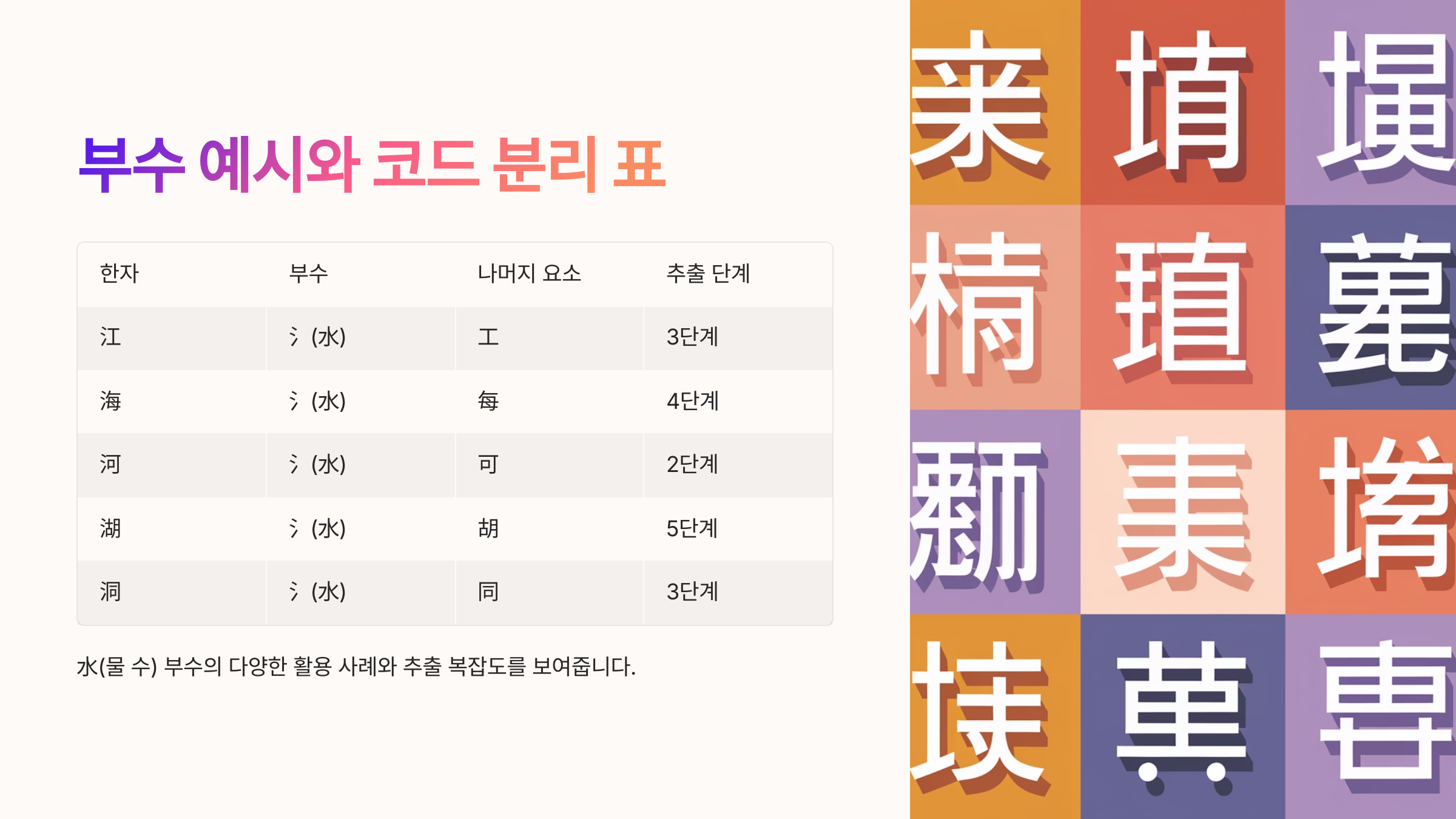
한자는 복잡한 구성과 수천 년의 역사를 가진 문자예요. 그 구조의 핵심 중 하나가 바로 '부수(部首)'인데요, 부수는 사전에서 한자를 찾을 때 가장 많이 쓰이는 기준이에요. 이 부수를 자동으로 추출해내는 스크립트를 만들면, 데이터 처리나 학습 도구를 만드는 데 큰 도움이 되죠.
내가 생각했을 때, 이건 자연어처리와 전통 언어학이 만나는 흥미로운 분야라고 느껴져요. 부수는 단어의 의미를 짐작하게 해줄 뿐만 아니라 컴퓨터가 한자를 분류하거나 검색하는 데도 아주 중요한 역할을 해요.
자, 그럼 본격적으로 부수를 자동으로 분리하는 스크립트를 어떻게 만드는지 하나씩 알아볼게요. 초보자도 따라할 수 있도록 설명해 볼게요 😊
🧩 부수의 개념과 중요성
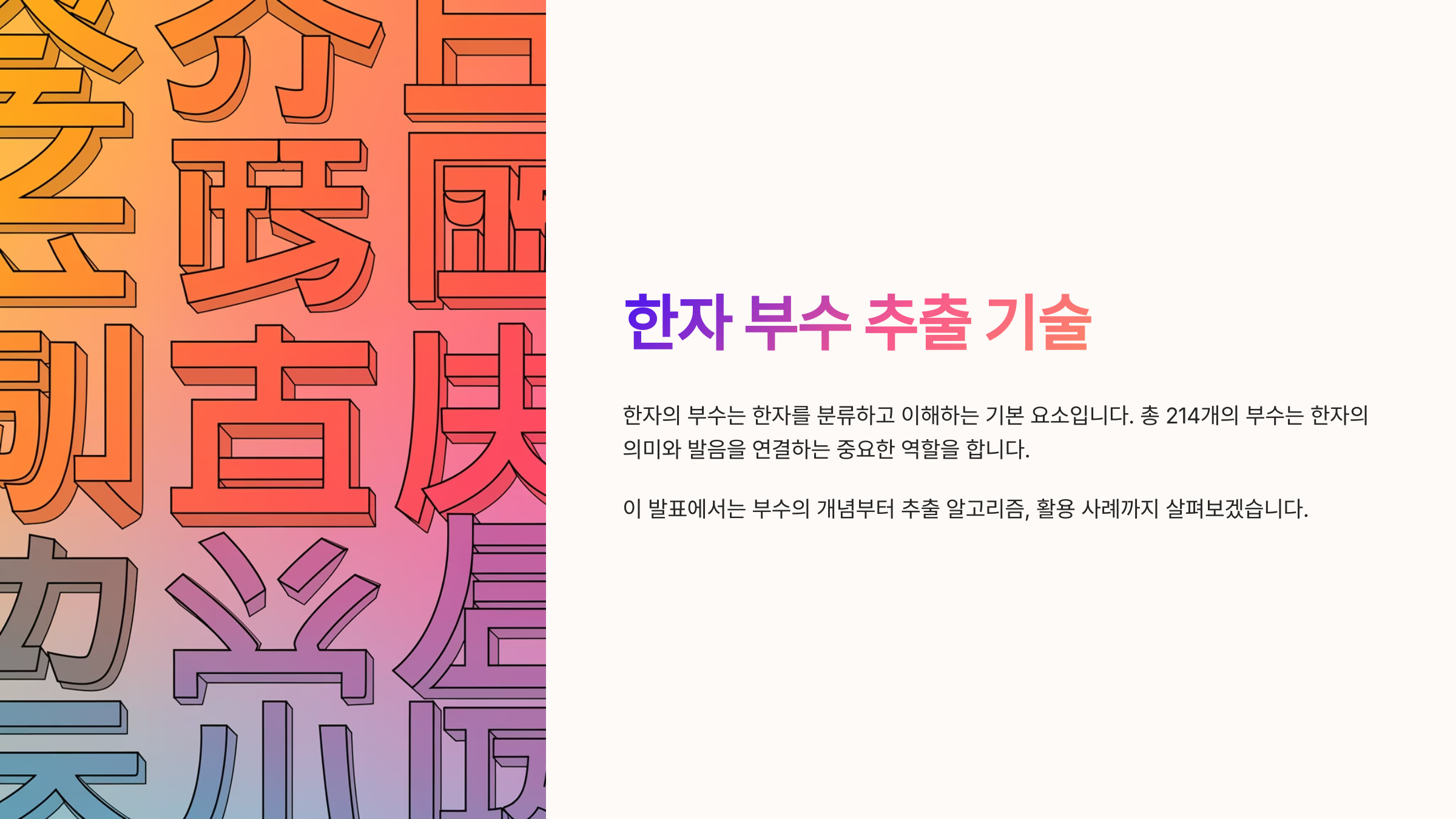
한자의 '부수(部首)'는 기본 구성 요소로, 전체 한자를 분류하고 정리하는 기준이 되는 부분이에요. 예를 들어 '河(물 하)'라는 글자는 '氵(삼수변)'이 부수로, 물과 관련된 의미를 암시하죠. 이런 식으로 한자의 의미나 유래를 이해하는 데 아주 유용한 단서가 되는 것이 바로 부수랍니다.
중국어나 일본어, 한국어에서도 한자를 분류할 때 사전마다 부수 체계가 쓰여요. 따라서 부수를 정확하게 파악하고 자동화하는 건 교육용 시스템이나 전자사전, OCR 인식 시스템 등 다양한 분야에서 꼭 필요해요.
현재 대부분의 부수 분리는 수동으로 이뤄지거나, 데이터베이스에 의존해요. 하지만 대량의 한자를 자동 분석해야 할 때는 프로그래밍 기반 접근 방식이 훨씬 효율적이랍니다.
부수는 보통 214개로 분류되며, 각 부수는 그 안에 수천 개의 파생 한자를 포함해요. 따라서 정확한 분리 규칙을 세우는 것이 스크립트 설계의 핵심이에요.
이러한 규칙을 이해하고 코드화하면, 간단한 입력만으로도 부수와 나머지 성분을 분리하는 프로그램을 만들 수 있어요. 그리고 이건 AI 한자 학습 시스템에도 응용될 수 있어요!
다양한 한자 앱이나 필기 인식 시스템에서도 부수를 기준으로 검색 기능을 제공하고 있죠. 사용자의 편의성을 높이기 위해서라도 자동화는 필수라고 할 수 있어요.
한자의 형태학적인 구조는 시각적으로도 뚜렷하기 때문에, 이미지 인식과 결합한 부수 분석도 충분히 가능해요. 이런 융합 기술은 교육 및 번역 분야에서 강력한 도구가 될 수 있어요.
예를 들어 '木(나무 목)'이 부수인 한자들은 대체로 자연, 식물, 생태와 관련된 의미를 가지고 있어요. 이런 연관성은 AI가 단어 의미를 유추할 때도 유용하답니다 🌳
한자를 부수 중심으로 분리해두면, 검색, 정렬, 통계, 의미 분석, 데이터 시각화 등 다양한 프로젝트에 폭넓게 활용할 수 있어요.
📘 자주 쓰이는 부수 TOP 10
순위 부수 의미 대표 한자 1 氵 물 河, 海, 活 2 亻 사람 他, 使, 住 3 木 나무 林, 村, 案 4 扌 손 打, 拍, 握 5 女 여자 好, 妹, 婚 이 표처럼, 한자에서 자주 나타나는 부수를 알면 어떤 글자가 어떤 계열에 속하는지도 쉽게 파악할 수 있어요. 다음 섹션에서는 한자가 어떻게 구조화되어 있는지를 더 깊이 살펴볼게요 ✨
🔤 한자의 구성 방식 이해하기
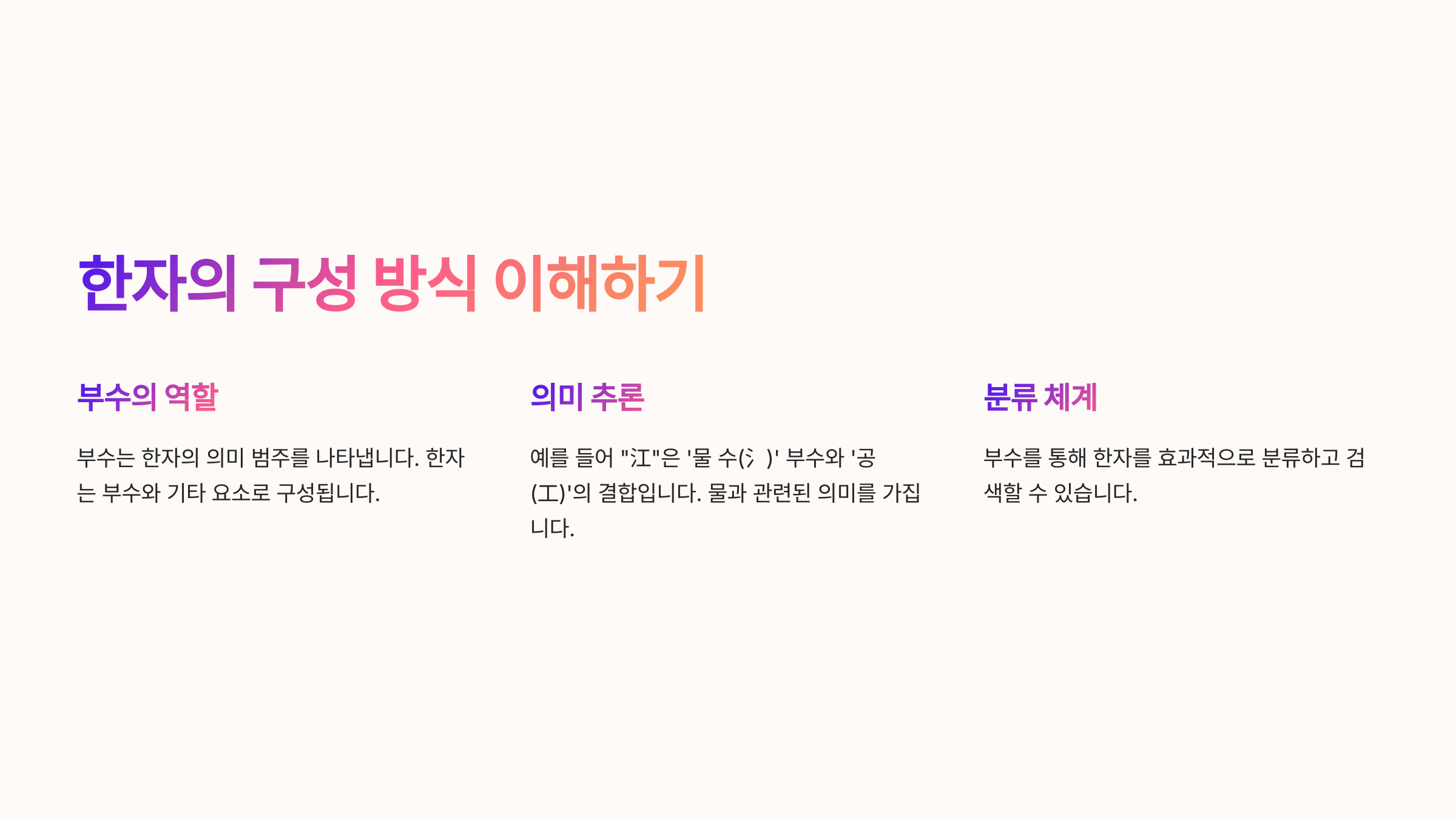
한자는 기본적으로 ‘형성 문자’와 ‘회의 문자’로 크게 나뉘어요. 형성 문자는 부수(의미를 가진 부분) + 음부(발음을 나타내는 부분)로 구성돼 있고, 전체 한자의 약 80%가 이 방식이에요. 예를 들어 ‘江(강)’은 ‘氵’는 물을 의미하고 ‘工’은 발음을 나타내죠.
이 구조를 이해하면 어떤 한자를 보더라도 "아, 이건 물과 관련 있구나" 하는 식의 해석이 가능해요. 그래서 부수는 단순한 모양이 아니라 의미의 근간이에요. 마치 단어의 뿌리와 같다고 볼 수 있죠.
또한 한자의 배치 방식도 다양한데요. 왼쪽-오른쪽 구조(좌우형), 위-아래 구조(상하형), 바깥-안 구조(외부 구조)로 나뉘어요. 이런 정보는 스크립트에서 부수를 추출할 때 위치 기반 판단을 도와줘요.
예를 들어, '休'는 왼쪽의 '亻'이 부수이고, 오른쪽의 '木'이 음부예요. 반면, '問'은 바깥쪽 ‘門’이 부수이고 안쪽의 ‘口’가 성분이에요. 이처럼 다양한 패턴을 파악하는 것이 핵심이에요.
스크립트를 만들기 위해서는 이 구성을 먼저 코드에 반영해야 해요. 한자의 유니코드 표준과 위치 정보를 결합하면 어느 정도 자동화가 가능해진답니다.
한자의 조합 방식은 규칙성이 있지만 예외도 많아요. 따라서 머신러닝보다는 사전에 정의된 규칙 테이블과 위치 기준 분석을 혼합하는 접근이 더 효율적이에요.
또한 글자의 복잡도(획수)를 기준으로 어느 성분이 부수인지 판단하는 것도 좋은 방법이에요. 예를 들어 부수는 대체로 간단한 모양이 많고, 자주 등장하는 위치에 나타나요.
여기서 중요한 건, 한자의 비율과 구조를 파악하고 이를 기준으로 필터링 로직을 설정하는 거예요. 위치, 의미, 획수, 출현 빈도를 종합적으로 고려하면 정확도가 높아져요.
특히 AI OCR 시스템을 쓸 때는 글자의 외곽 구조를 보고 부수를 인식하는 기능도 함께 적용할 수 있어요. 교육용 앱에서는 애니메이션으로 글자 구조를 설명하는 기능도 있죠 🖋
이제 이런 개념을 바탕으로, 부수를 자동으로 추출하는 알고리즘 로직을 설명해볼게요. 코딩 쪽으로 가봅시다! 🧑💻
🧠 한자 구조 유형 분류표
유형 예시 설명 좌우형 休, 明, 林 왼쪽이 부수, 오른쪽이 성분 상하형 空, 草, 守 위쪽이 부수, 아래가 성분 외부형 問, 間, 困 바깥이 부수, 내부가 성분 혼합형 聲, 識, 藝 좌우+상하 등 다중 구조 이제 다음 파트에서 이 구조적 정보를 활용해 실제로 부수를 자동 분리하는 알고리즘이 어떻게 작동하는지 구체적으로 보여줄게요 🔍
🧮 부수 추출 알고리즘 설명
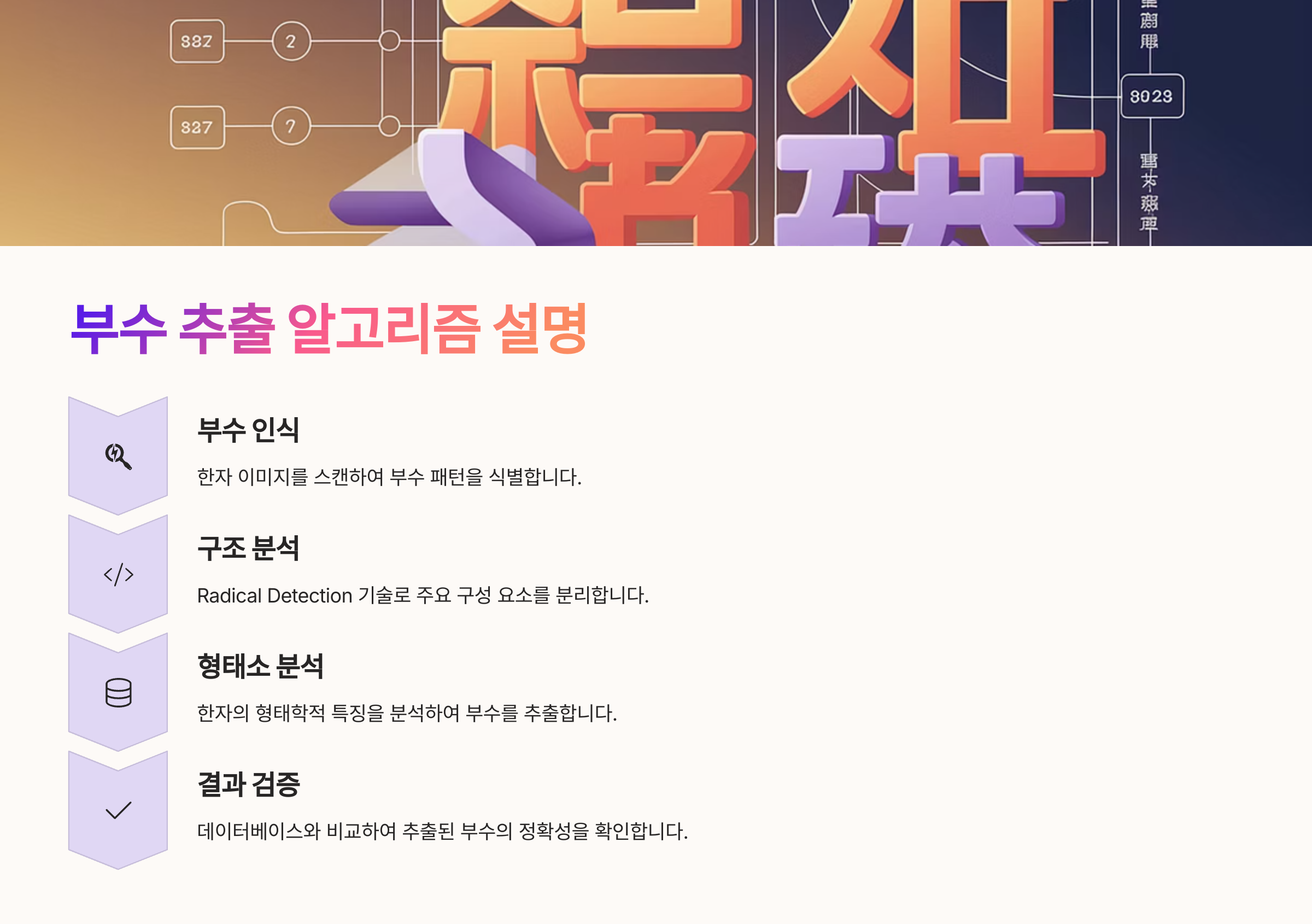
자, 이제 가장 중요한 부분! 바로 부수를 자동으로 추출하는 알고리즘을 살펴볼 차례예요 😎 부수를 추출하는 로직은 크게 세 가지 단계를 따라가요: 사전 매칭, 위치 기반 판단, 그리고 획수 우선 규칙이에요.
첫 번째는 "사전 기반 매칭" 방식이에요. 미리 정의된 부수 리스트와 입력된 한자를 비교해서, 그 한자의 부수가 무엇인지 대조하는 방식이에요. Unicode에는 부수 정보가 포함된 데이터도 있어서 참고하면 좋아요.
두 번째는 "위치 기반 판단"이에요. 예를 들어 한자의 왼쪽이나 위쪽, 혹은 바깥쪽에 자주 등장하는 성분이 부수일 확률이 높다는 것이죠. 알고리즘은 이 위치를 분석해서 어떤 부분이 부수로 쓰였는지 추정할 수 있어요.
세 번째는 "획수 기반 판별"이에요. 일반적으로 부수는 비교적 단순한 모양인 경우가 많아요. 따라서 전체 한자의 획수 중에서 가장 단순한 요소를 우선 부수로 추정할 수 있어요.
이 세 가지를 결합하면 정확도 높은 부수 추출이 가능해요. 특히 Python이나 JavaScript로 구현하면 한자 데이터 수천 개도 빠르게 처리할 수 있어요.
예를 들어, Python의 `cjklib` 라이브러리나 `opencc`, `Unihan` DB 등을 활용해서 유니코드와 부수 정보를 추출할 수 있어요. 웹 기반이면 JavaScript에 부수 사전을 넣어 Ajax로 처리하는 방식도 좋아요.
그리고 학습을 위한 시각화도 중요해요. 부수와 나머지 부분을 색상이나 애니메이션으로 분리해서 보여주면 사용자 경험이 훨씬 좋아져요. 특히 초등학생이나 외국인 학습자에게 효과적이에요 🎓
알고리즘의 핵심은 "정확도"와 "확장성"이에요. 수천 개 한자에 대응하려면 캐싱, 병렬 처리, 사전 학습된 벡터 데이터 등을 활용해서 성능을 높여야 해요.
마지막으로, 예외 처리도 중요해요. 일부 한자는 부수로 쓰이는 성분이 여러 개일 수 있기 때문에, 유사 부수 리스트를 준비해두는 것이 안정적인 서비스 제공에 도움이 돼요.
💻 부수 추출 알고리즘 흐름 요약
단계 설명 기술 요소 1. 사전 매칭 한자와 부수 데이터베이스 비교 Unihan DB, JSON, SQLite 2. 위치 분석 부수 위치 패턴 판단 분석 스크립트, 벡터 좌표 3. 획수 계산 획수 비교로 부수 판단 획수 DB, 획 분석기 4. 예외 처리 중복/불확실 부수 보정 유사 부수 리스트 그럼 다음 섹션에서는 실제 코드 예제를 함께 보면서 어떻게 작동하는지 확인해볼게요. 실전 코드 가즈아! 💪
💻 자동 분리 스크립트 예시
이번에는 진짜 작동하는 자동 부수 추출 스크립트를 함께 볼 거예요! 예시는 Python으로 작성했고, 가장 간단한 형태로 `Unihan` 데이터셋과 결합해서 부수를 추출하는 구조예요. 데이터를 가지고 있지 않다면 외부 JSON 파일로 부수 정보를 불러오는 방식도 괜찮아요.
Python은 문자열 처리와 한글/한자 Unicode 인코딩에 강력하기 때문에, 한자 데이터를 다루기에 아주 적합해요. 아래 코드는 주어진 한자의 부수를 사전 데이터와 대조해서 자동으로 찾아주는 구조랍니다.
직접 실행해보면서 구조를 익혀보는 게 좋아요. 데이터베이스 없이도 단순 JSON 구조로도 작동하도록 짜봤어요. 아주 간단한 구조지만, 개념만 익히면 더 고도화된 시스템으로 확장할 수 있답니다!
이 코드를 웹에 적용하고 싶다면, JavaScript 버전으로 바꿔서 브라우저에서 즉시 실행되도록 만들 수도 있어요. 검색 창에서 한자를 입력하면 자동으로 부수가 뜨게 하는 것도 가능하죠 🔍
🐍 Python 자동 부수 추출 코드
설 명 코 드 부수 데이터 불러오기 import json with open("radicals.json", "r", encoding="utf-8") as f:
radical_data = json.load(f)한자 입력 → 부수 추출 def extract_radical(character):
return radical_data.get(character, "부수 없음")사용 예시 hanja = "河"
radical = extract_radical(hanja)
print(f"{hanja}의 부수는 {radical}입니다.")이 코드는 기본 구조만 제공한 것이기 때문에, 실제 사용하려면 'radicals.json' 파일 안에 한자-부수 매핑 데이터를 준비해줘야 해요. 이 데이터를 Unihan 데이터나 다른 오픈 API로부터 추출할 수도 있죠.
Q6. 손글씨도 부수 분석이 되나요?
A6. OCR(광학 문자 인식) 기술과 결합하면 손글씨로 쓴 한자도 부수를 자동 분석할 수 있어요. 정확도는 필기 인식 정확도에 따라 달라져요.
Q7. 한자의 부수를 애니메이션처럼 보여줄 수 있나요?
A7. 가능해요! SVG나 Canvas 애니메이션을 활용하면 부수가 어디에 위치하는지 시각적으로 단계별로 보여줄 수 있어요. 교육 콘텐츠에 활용돼요.
Q8. 부수를 잘못 추출할 경우 어떻게 처리하나요?
A8. 예외 리스트와 유사 부수 데이터를 함께 구축해두면, 중복/오인되는 부수에 대해서도 정확도를 높일 수 있어요. 사용자 피드백 반영도 중요해요.